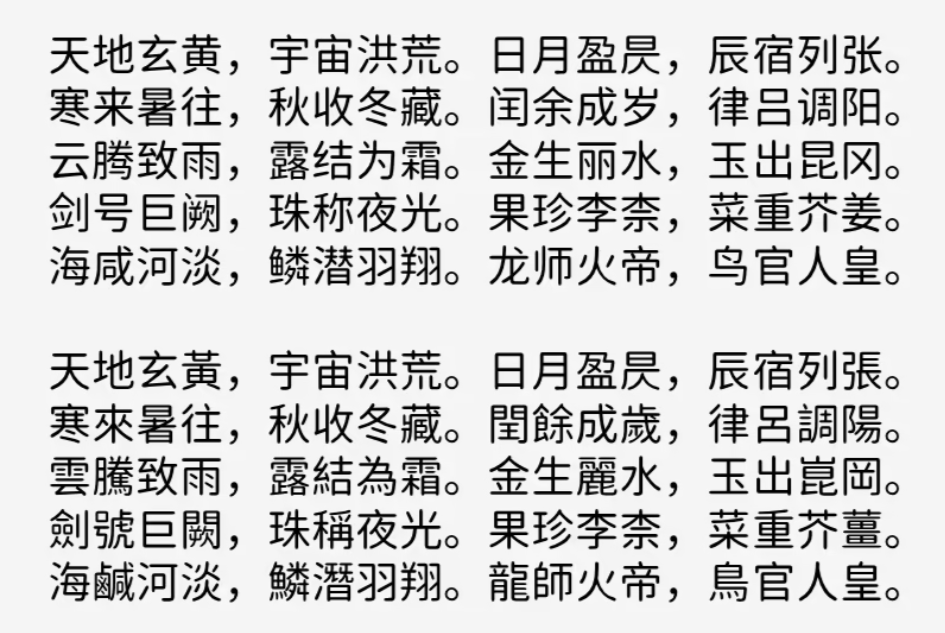
资源圆体(Resource Han Rounded)是由国内设计师Cyano Hao基于思源黑体改造而成的一款免费可商用圆体字体。它是将思源黑体直接变圆版,保留了其字体特征,然后将笔画末端的直角改成了圆角,使字体风格看起来更柔和。
资源圆体针对简体中文进行了专门的优化,涵盖了 30887 个字符和 31032 个字形,基本不会出现缺字的情况。同时提供了 7 种字重,可以满足标题、正文等不同场景的排版需求,比如品牌设计、UI界面设计、电商广告、印刷出版等都有广泛的应用。